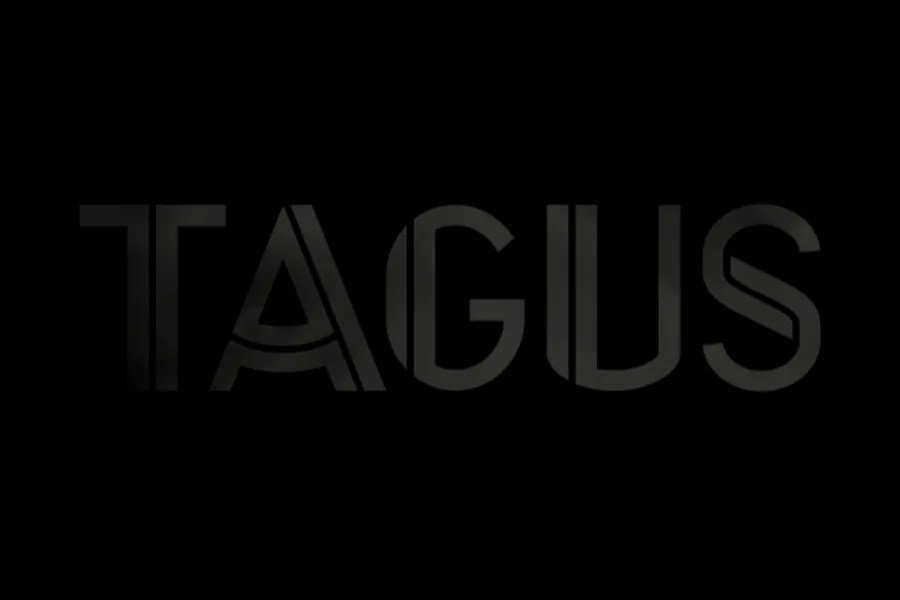
Introduzimos Tagus Display Free Typeface, uma nova escolha para designers e criadores de conteúdo que buscam uma fonte display moderna e versátil. Especificamente projetada por Hamilton, inspirada nos belos arquitectura japonês Kanji e na identidade visual de Azedo, a Tagus é uma opção divertida e fácil de usar. Com um design clean e elegante, a Tagus oferece uma combinação única de linhas finas e mais robustas que permite adaptar o tipo ao seu próprio estilo. Suas linhas fortes contrastam perfeitamente com as letras mais delicadas, permitindo criações multifacetadas. Seja para projetos gráficos em preto e branco ou cores vibrantes, a Tagus tem um lote de opções que se adequa ao seu design. A Tagus é uma excelente escolha para qualquer projeto que exija personalidade e destaque visual, seja para aplicações web, impressão ou mesmo materiais digitais. Sem dúvida, você não vai se arrepender de adquirir esta fonte free-type sem comprometer a qualidade do seu trabalho. Além disso, a Tagus é uma opção perfeita para designers que estão sempre buscando novas maneiras de expressar o design em suas criações visuais. Ela também pode ser facilmente personalizada e adaptada com ajustes de tamanho ou escala para atender às necessidades específicas do seu projeto. Se você está procurando por uma fonte free-type de alta qualidade, que oferece tanto um estilo atraente quanto uma versatilidade de uso, então a Tagus Display Free Typeface é um ótimo investimento. Não hesite em dar uma olhada e começar a experimentar agora!